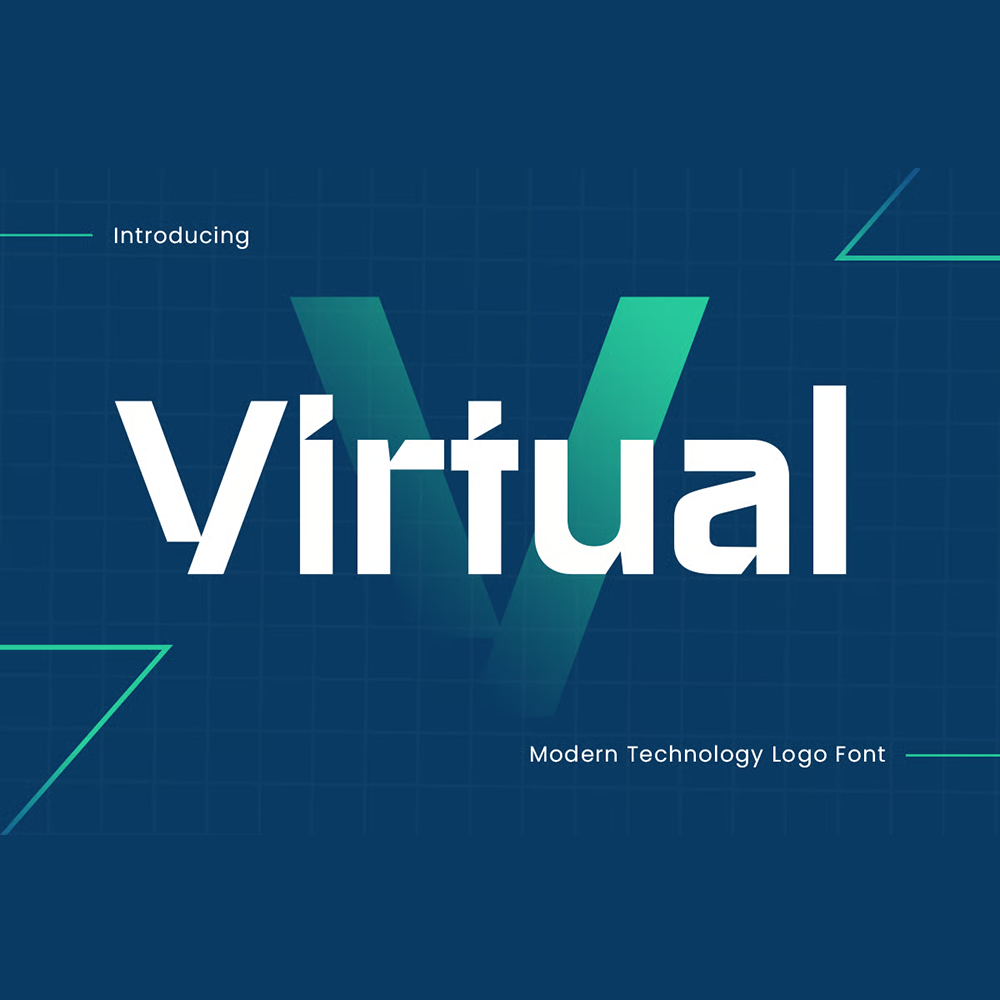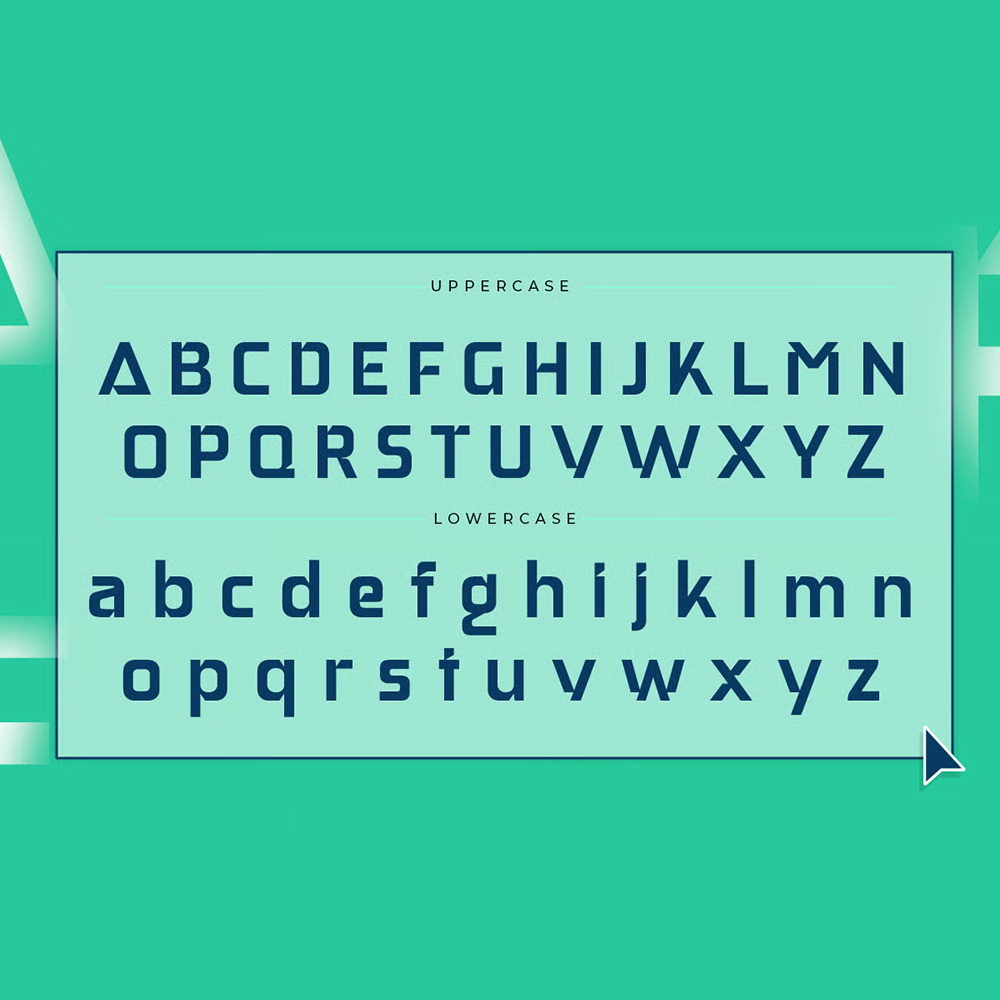
دانلود فونت انگلیسی Virtual Font
فونت پرمیوم و انگلیسی Virtual یک فونت لوگوی فناوری مدرن است که برای ایجاد جلوهای آیندهنگر در پروژههای برندسازی شما طراحی شده است. این فونت با الهام از خطوط براق فناوری پیشرفته، برای لوگوها، رابطهای دیجیتال و برندسازی که به ظاهری تمیز و نوآورانه نیاز دارند، ایدهآل است. Virtual با کاراکترهای فناوری منحصر به فرد و پشتیبانی چندزبانه، به راحتی با نیازهای مختلف طراحی سازگار میشود. این فونت با علائم نگارشی، اعداد، نمادها و کاراکترهای جایگزین، انعطافپذیری ارائه میدهد و طیف وسیعی از گزینههای خلاقانه را برای کار لوگو و برندسازی شما فراهم میکند.
مزایای استفاده از فونت لاتین Virtual Font چیست؟